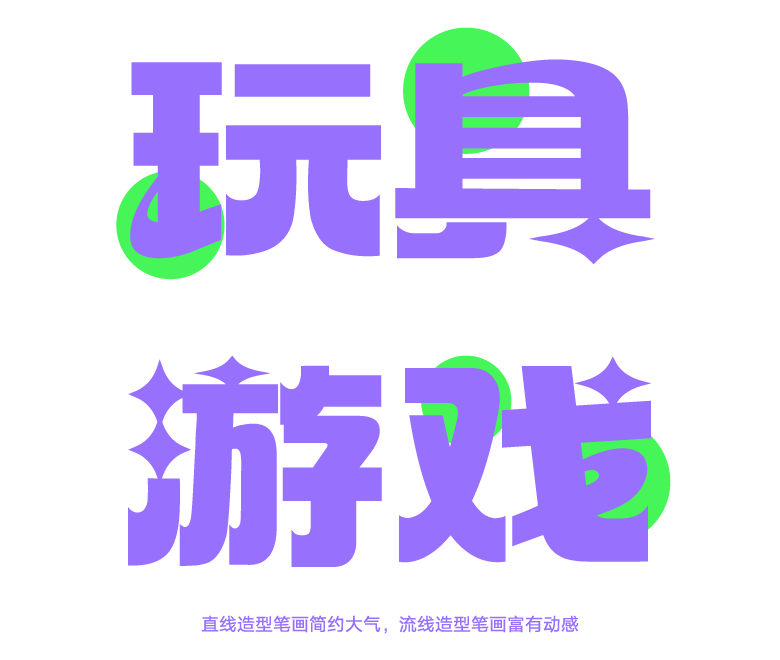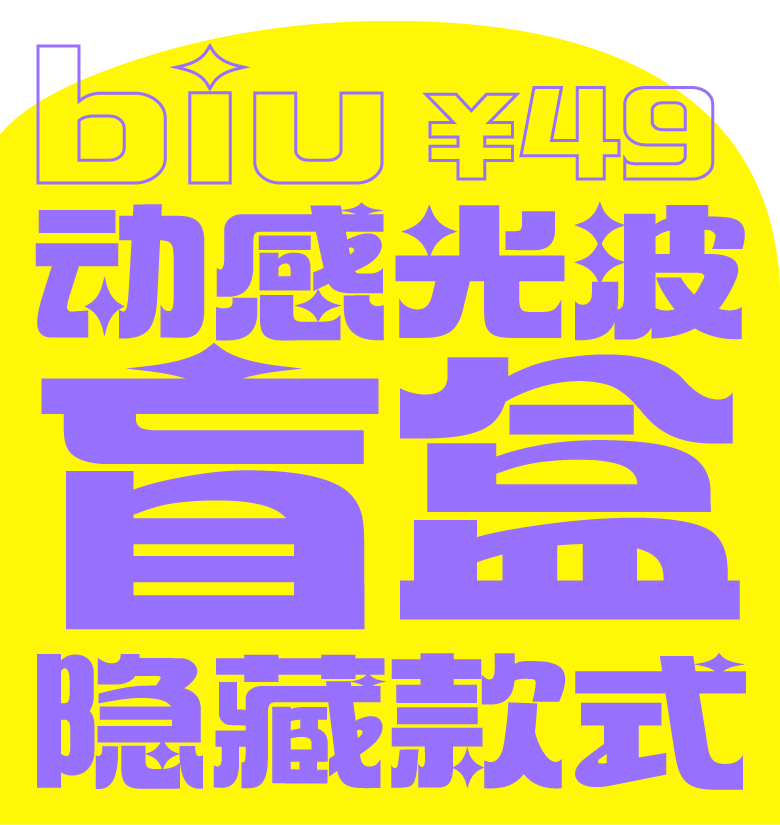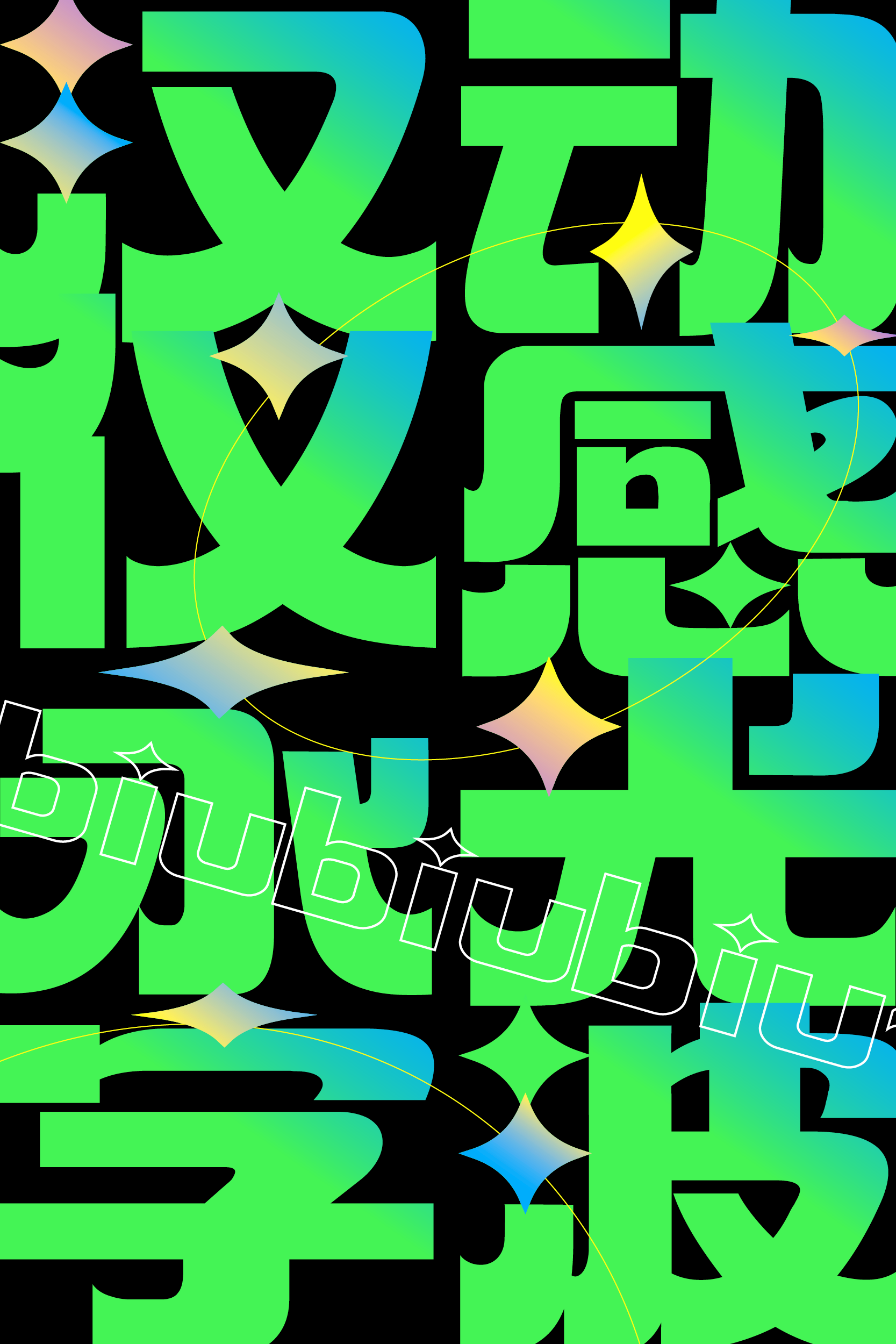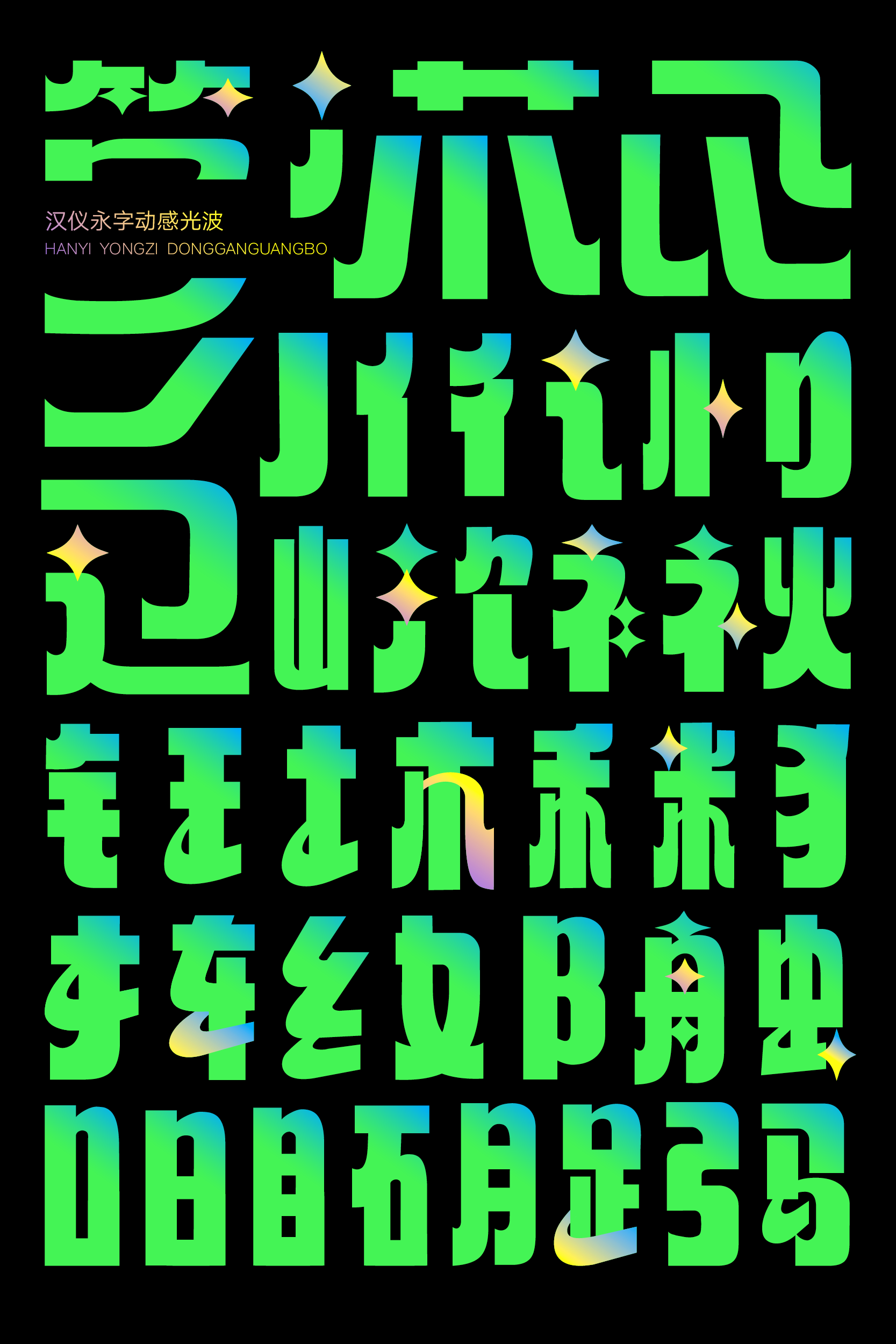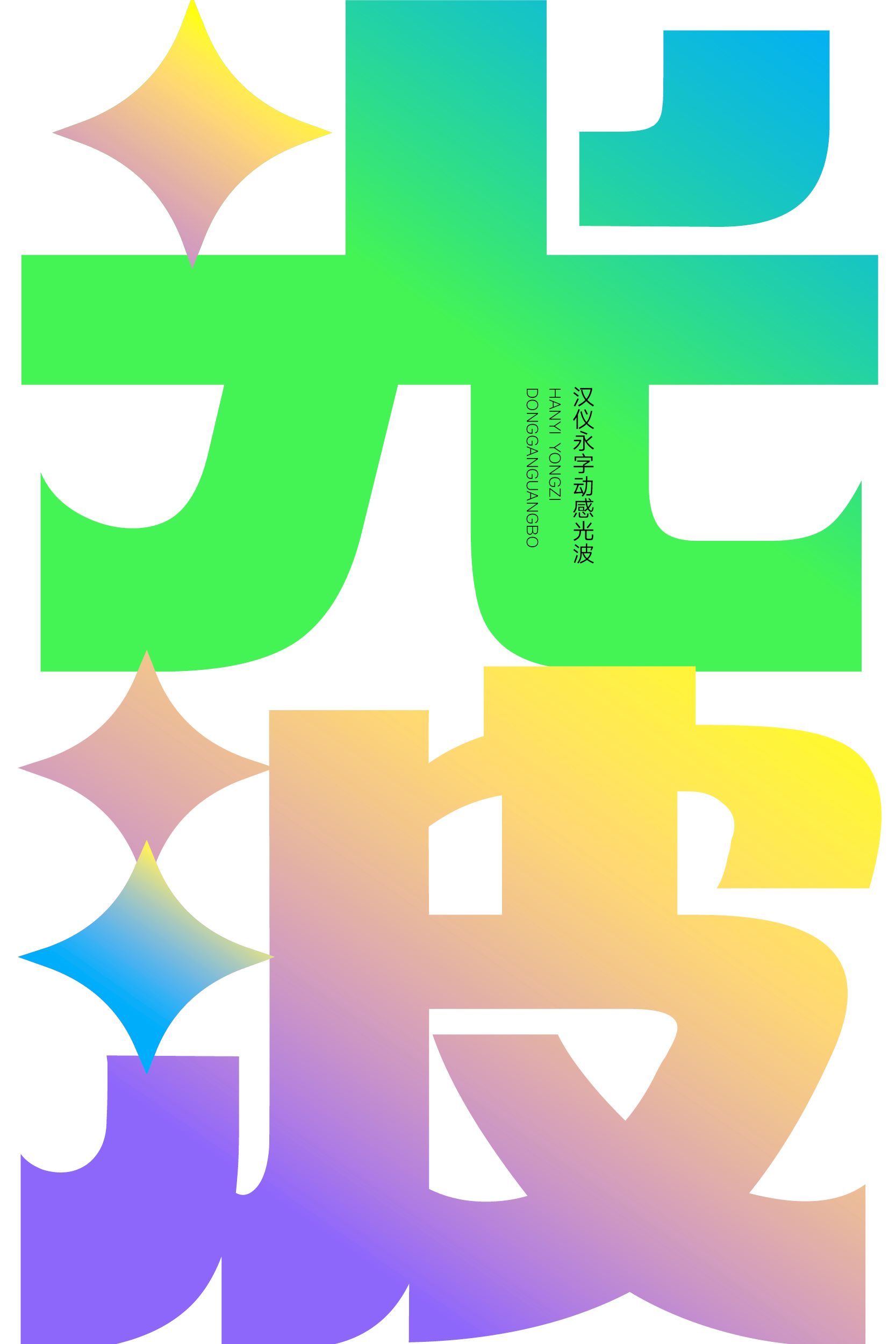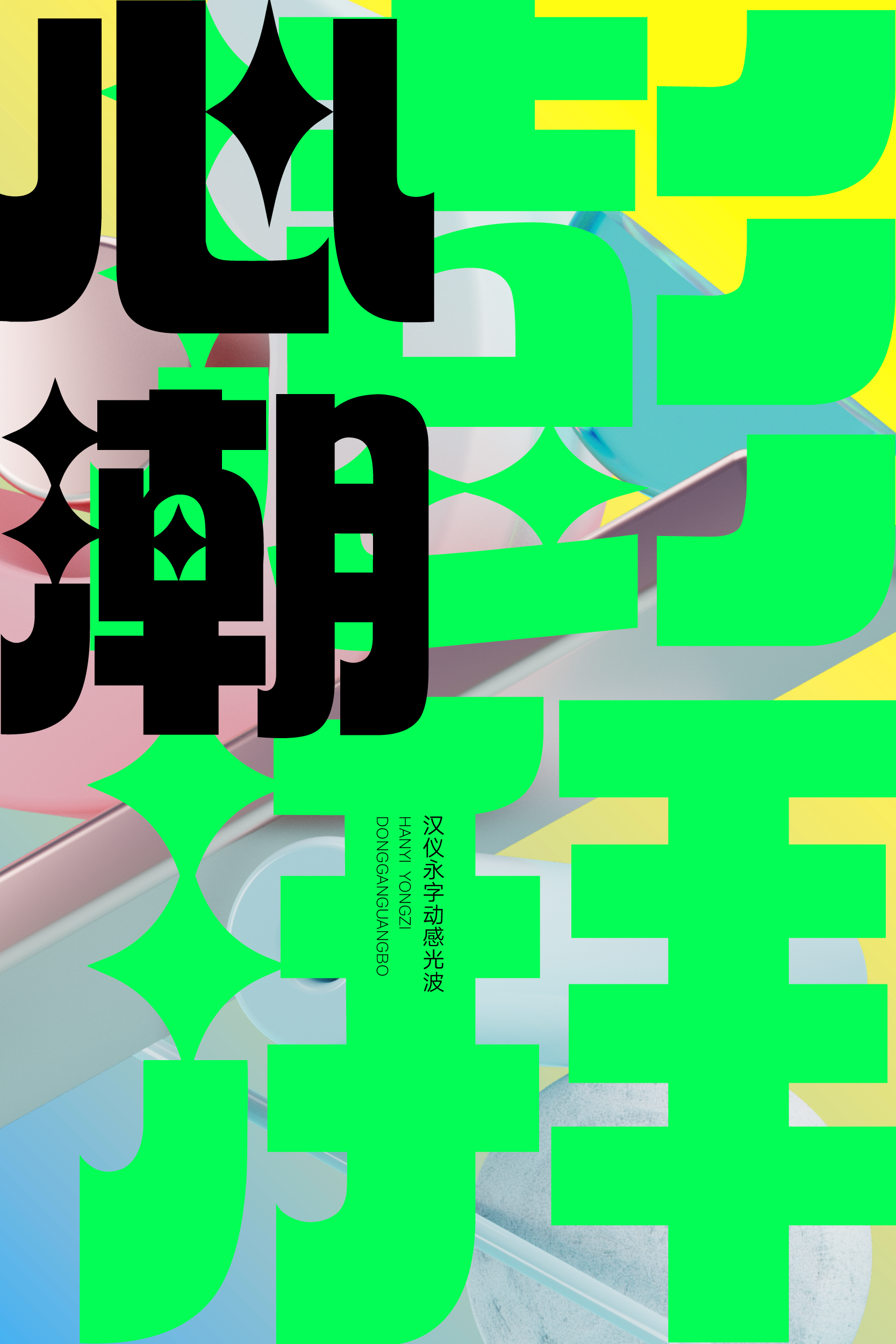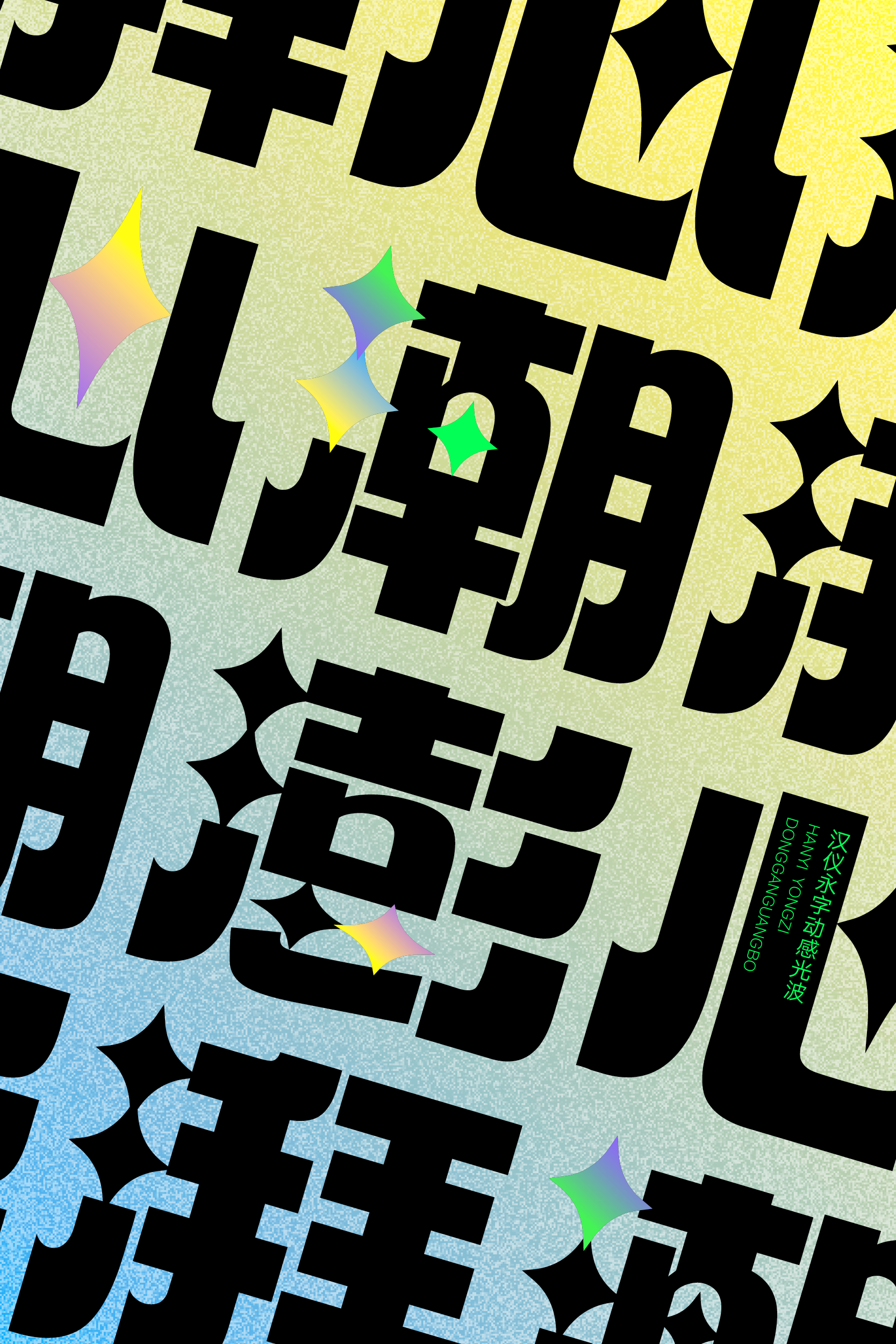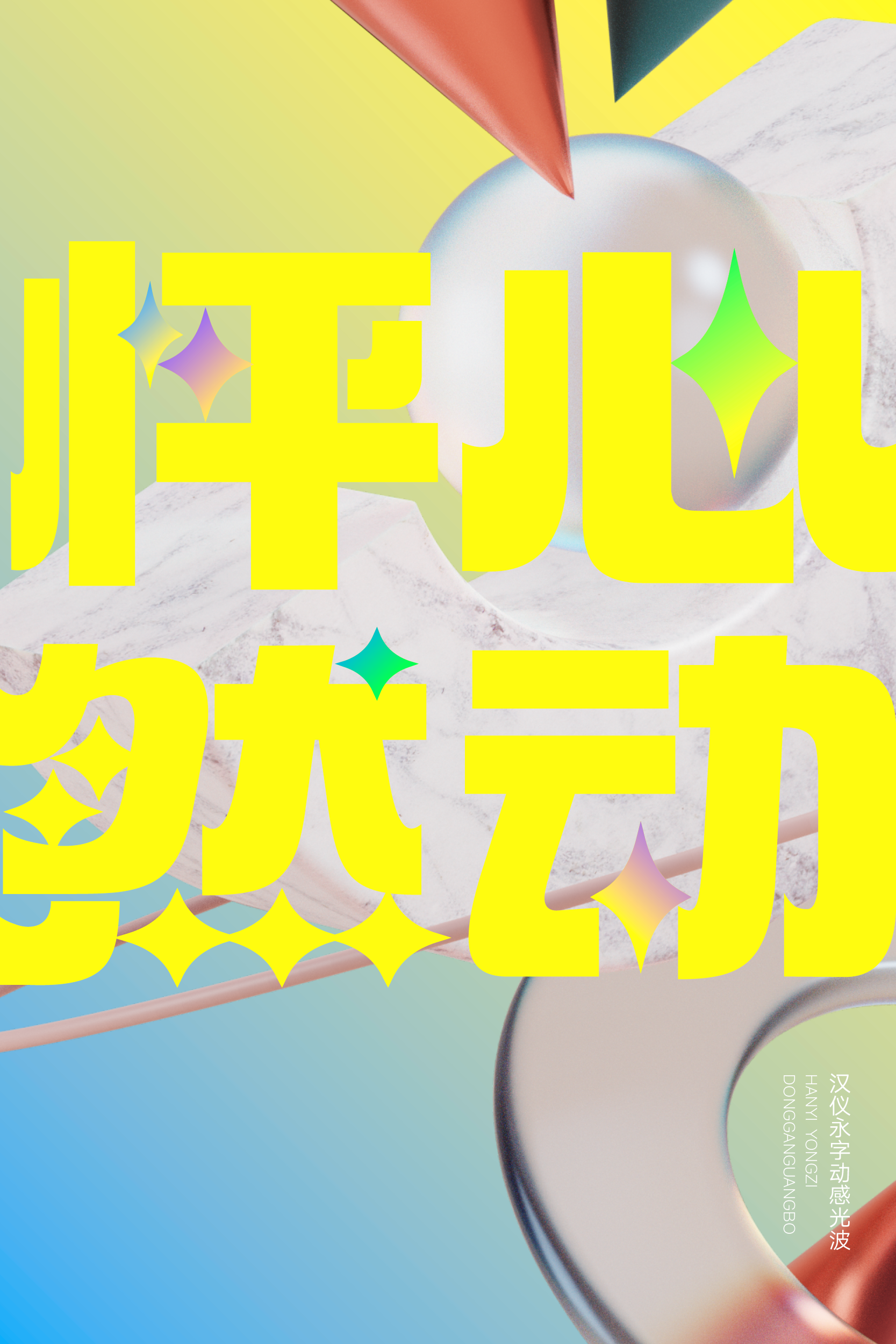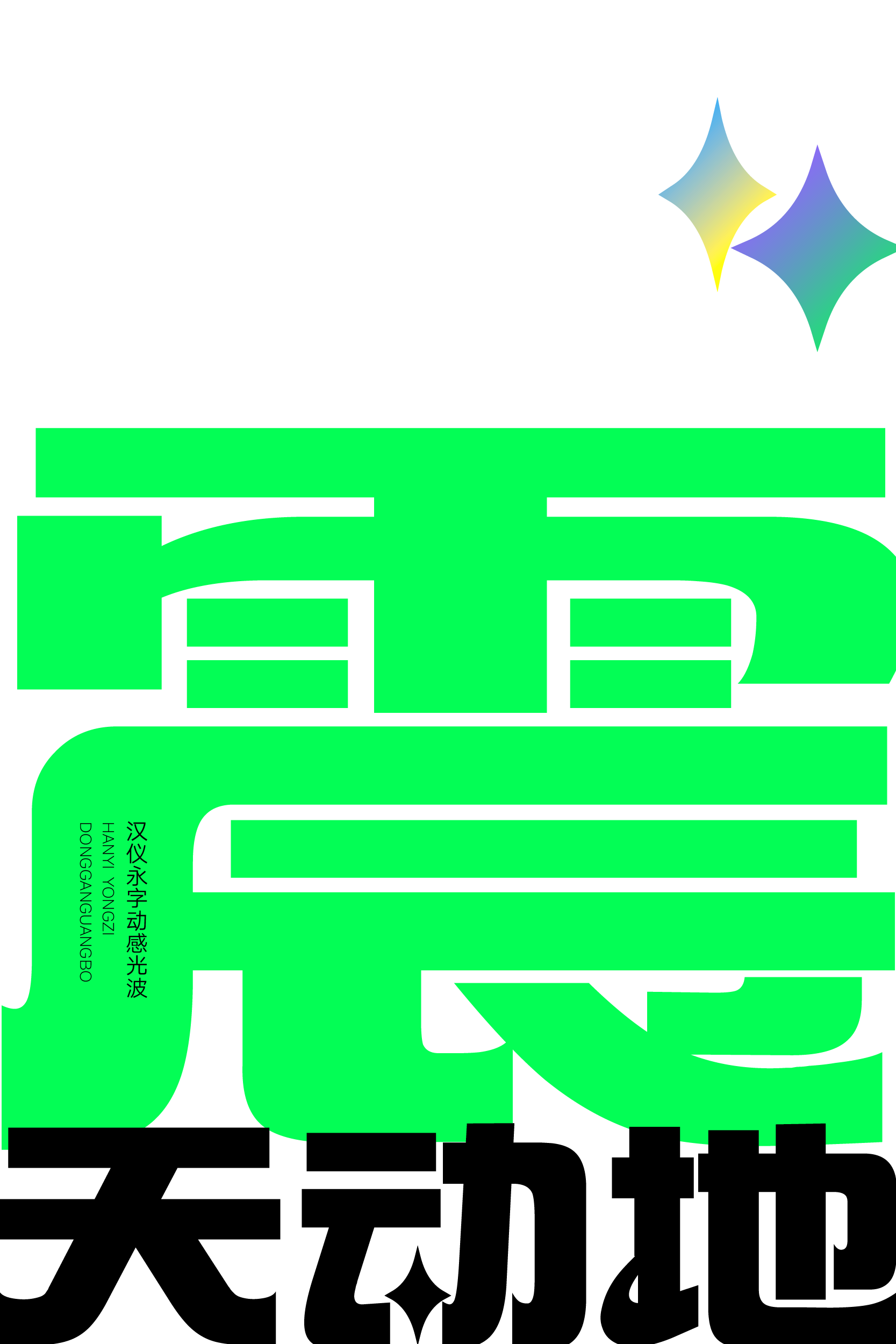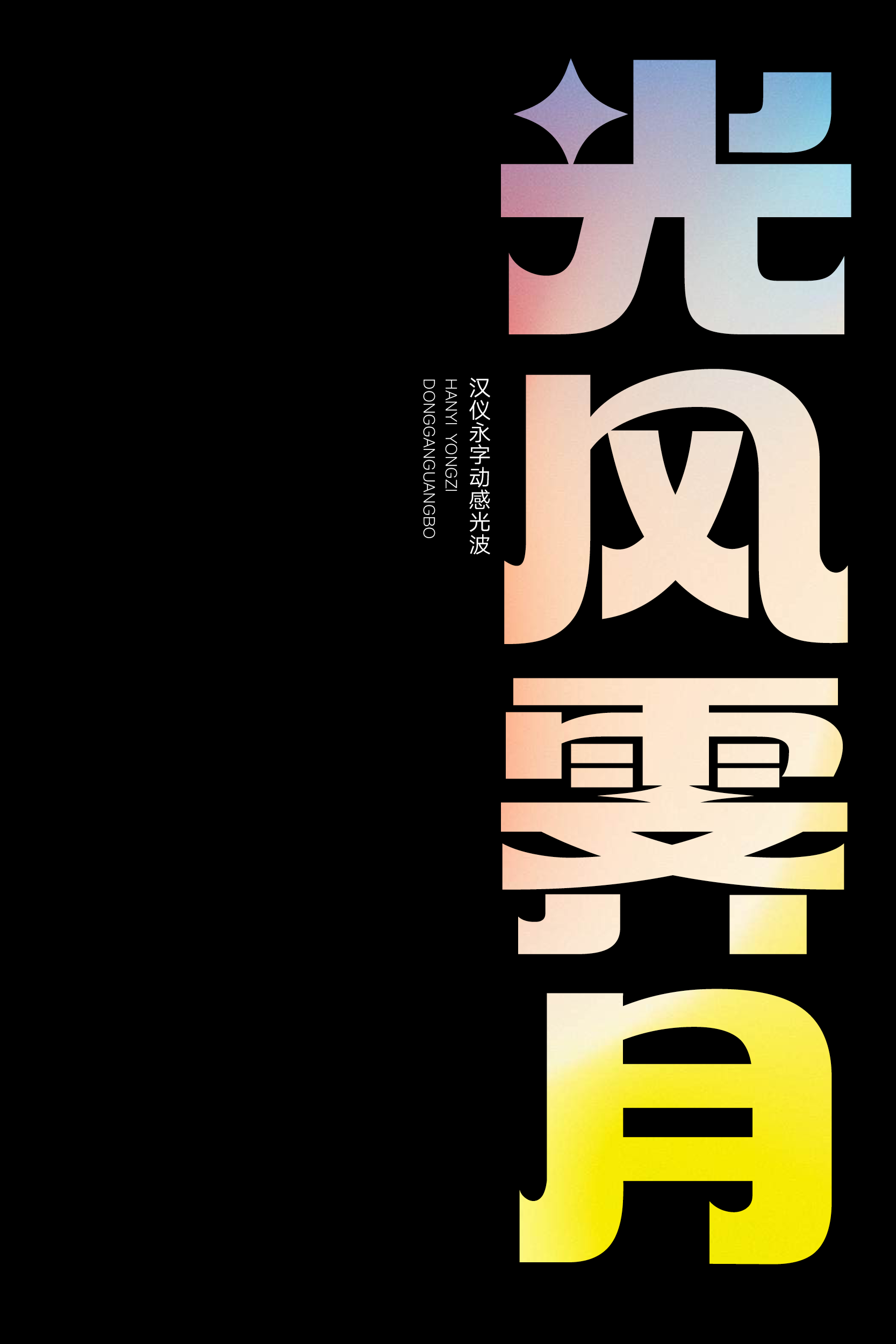
汉仪永字动感光波是由永字社创作的一款闪亮时尚的标题字体,字形简约,流线型笔画极具动感,星型笔画的点缀充满趣味。这款字体适合用于标题字体以及较短文本的排版,抓人眼球,在休闲娱乐、玩具周边等潮流时尚的使用场景中,用字体发射闪亮的动感光波!
字形扁方,方中带圆,造型简约现代。
直线造型笔画与流线造型笔画搭配,打造出时尚感。
点画变身闪亮的星星,撇捺收笔处的喇叭口处理与之呼应。
汉仪永字动感光波的西文部分以简约的无衬线体为基础,保留中文部分的字形和笔画设计语言。
汉仪永字动感光波是一款闪亮时尚的标题字体,自带潮流属性,搭配缤纷的色彩,与各类潮流玩具、时尚品牌有着极佳的匹配度。